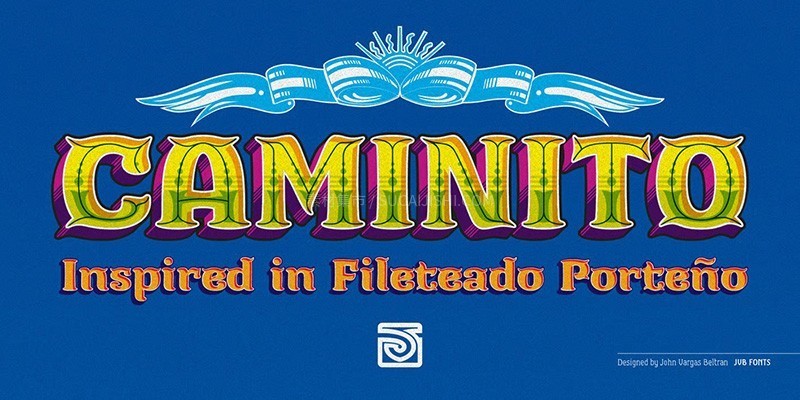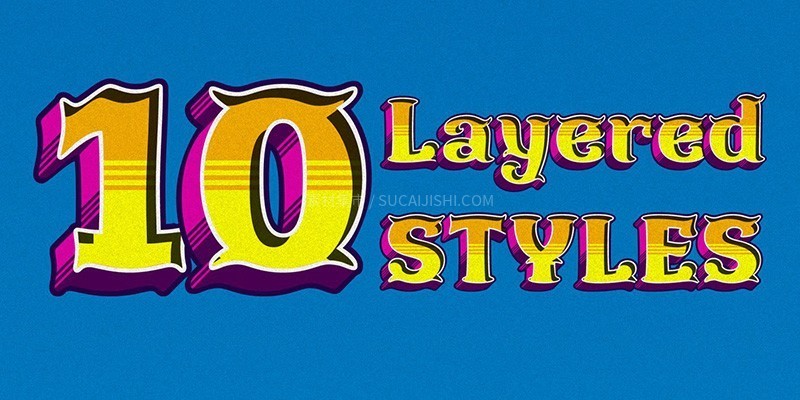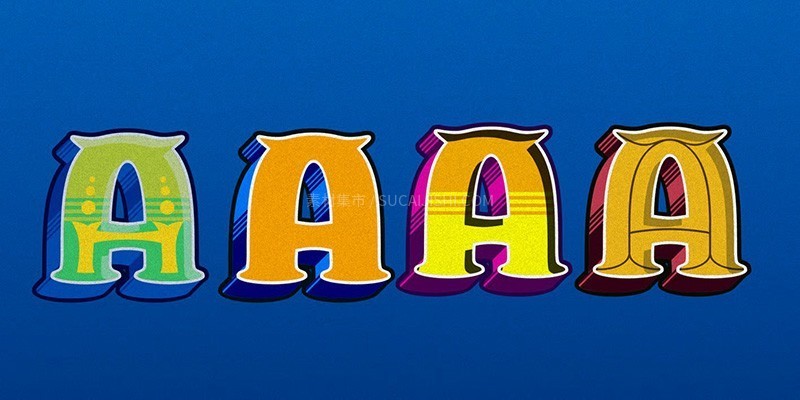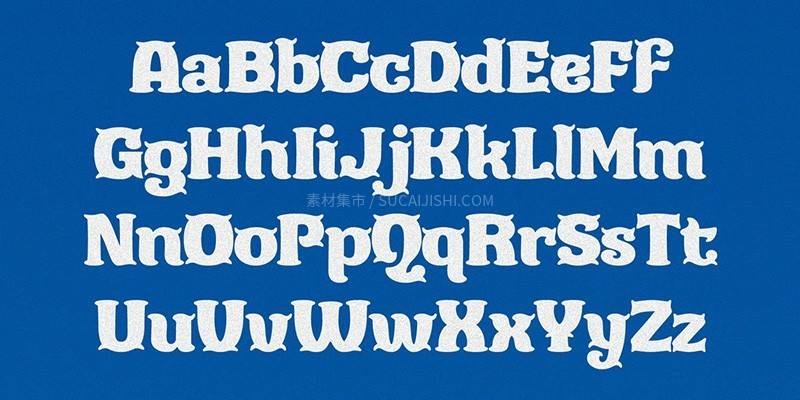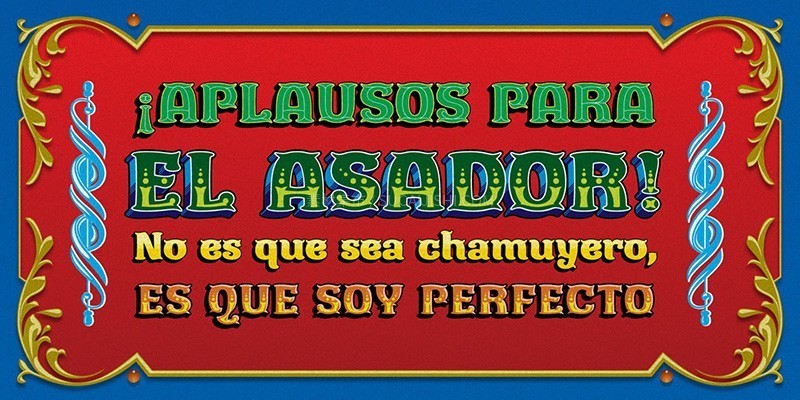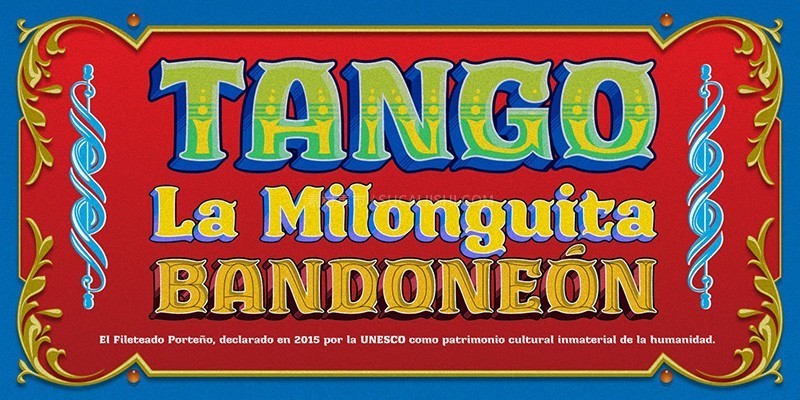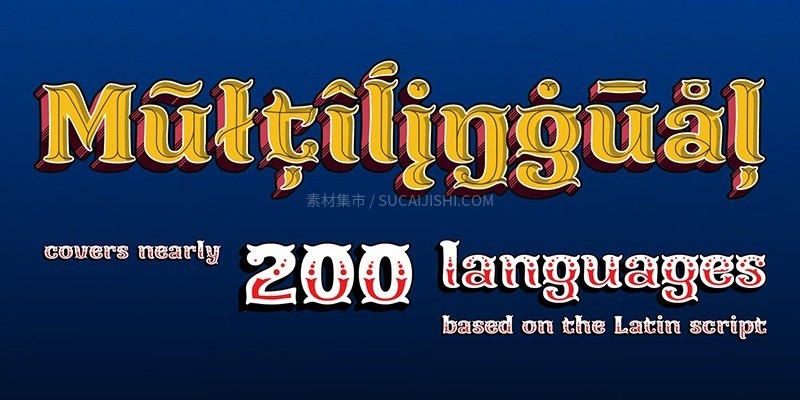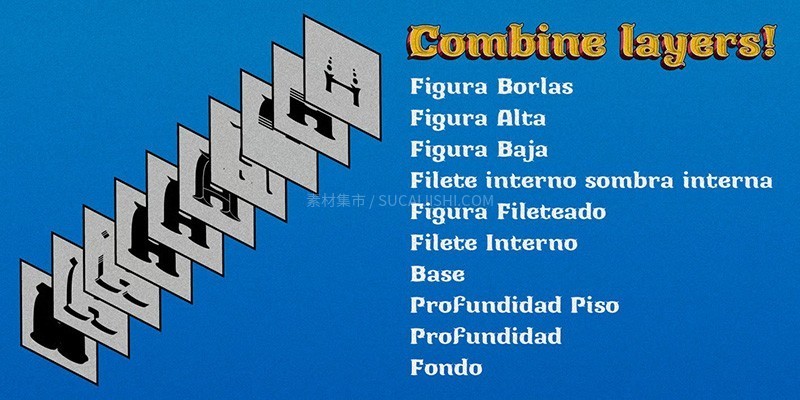
Caminito 阿根廷经典字体系列 (11种字重)
Caminito 是一款深受布宜诺斯艾利斯街头艺术与探戈文化启发的经典字体系列。全套包含 11 种字重,从纤细的线条到浓郁的粗体,完美融合了装饰艺术(Art Deco)的精致感与拉丁美洲的热情。其独特的曲线勾勒出复古且极具张力的视觉语言,是打造高辨识度品牌的理想选择。